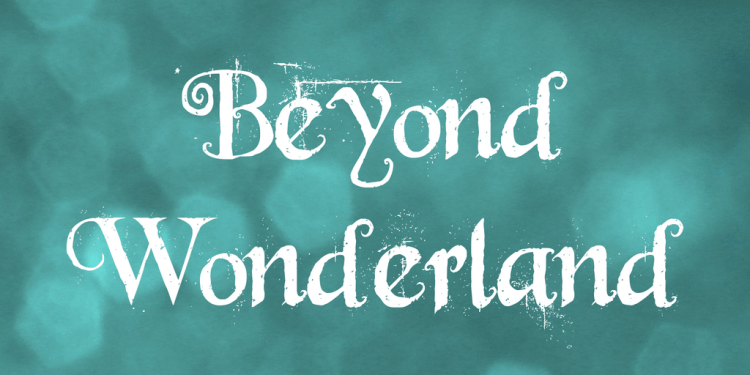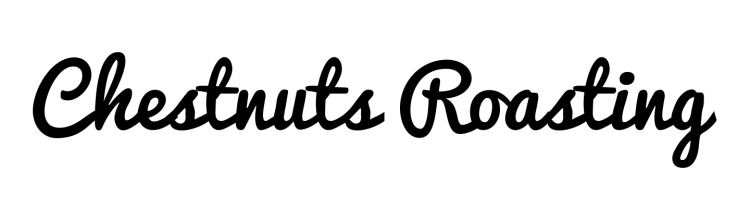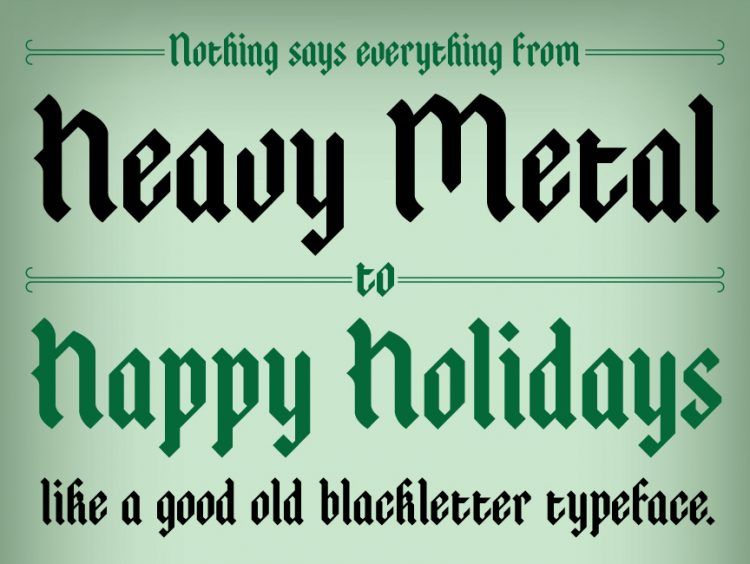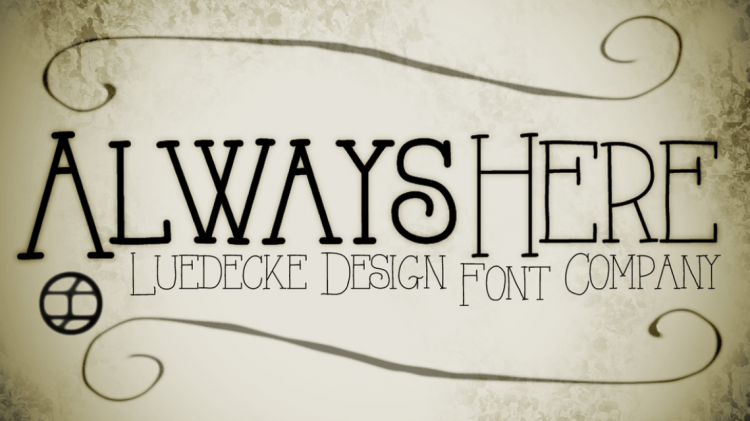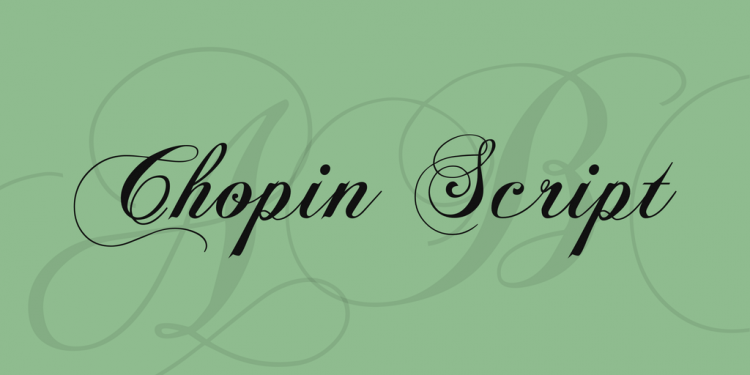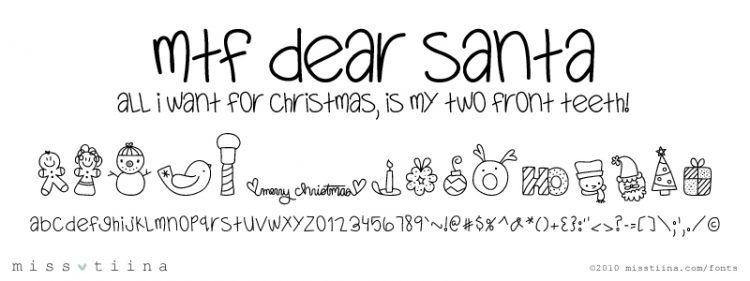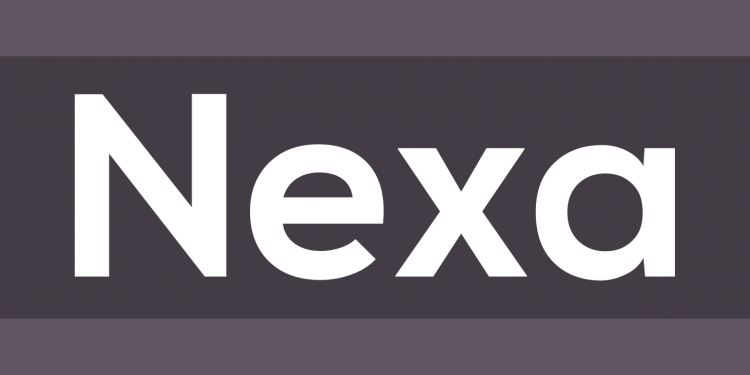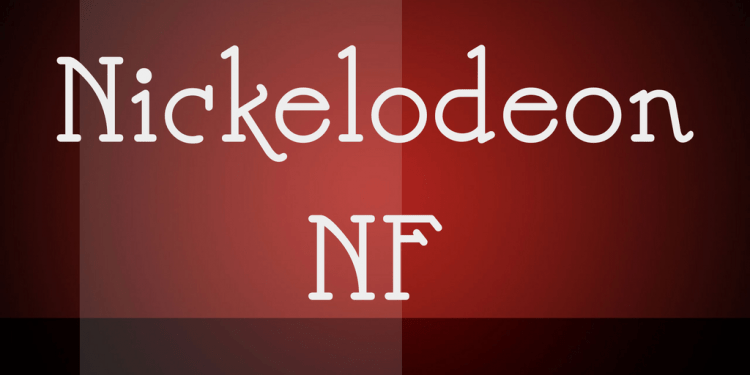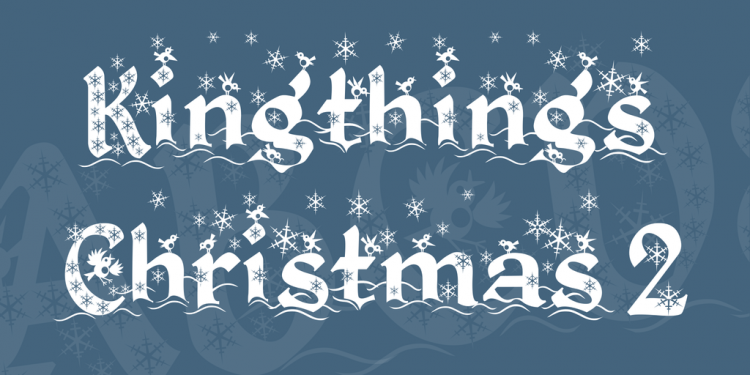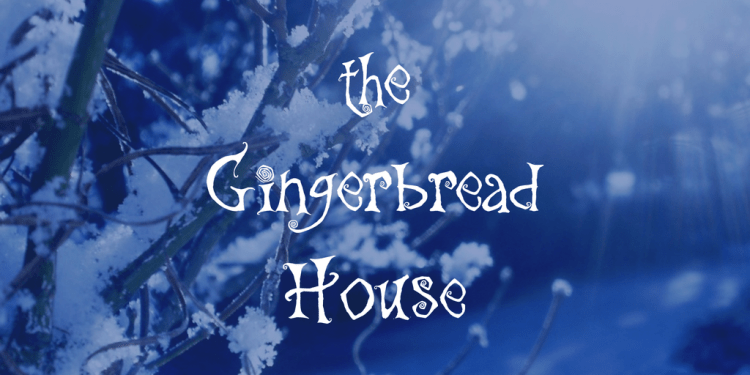
Se aproximan las fiestas y todo el mundo desea tener ligados sus proyectos para tal evento. Con tarjetas de felicitaciones, por ejemplo, podrás dar una gran bienvenida a tu proyecto.
La estética en Navidad es inconfundible y muy familiar, tanto es así que algunos diseñadores aprovechan para mostrar su talento con tipografías de este tipo de estilo, para que sinergizen con proyectos adaptados a tal fin.
Cuando estás buscando tipografías navideñas en la web, seguro que no deseas encontrarte con un set de tipografías caras. Por ello, aquí os muestro una gran cantidad de tipografías relacionadas con la Navidad y las fiestas, lo mejor es que son absolutamente gratis, hay unas 20, ¡echadles un vistazo!
Beyond Wonderland
St. Nicholas
Pacifico
Atreyu
Always Here
Chopin Script
MTF Dear Santa
Intrique Script
Nexa
Nickelodeon
Kingthing’s Christmas 2
The Gingerbread House
Alex Brush
Xmas Xpress
Candy Cane
One Starry Night
Olympic Branding
Marcelle Script
Sentinel
Frosty